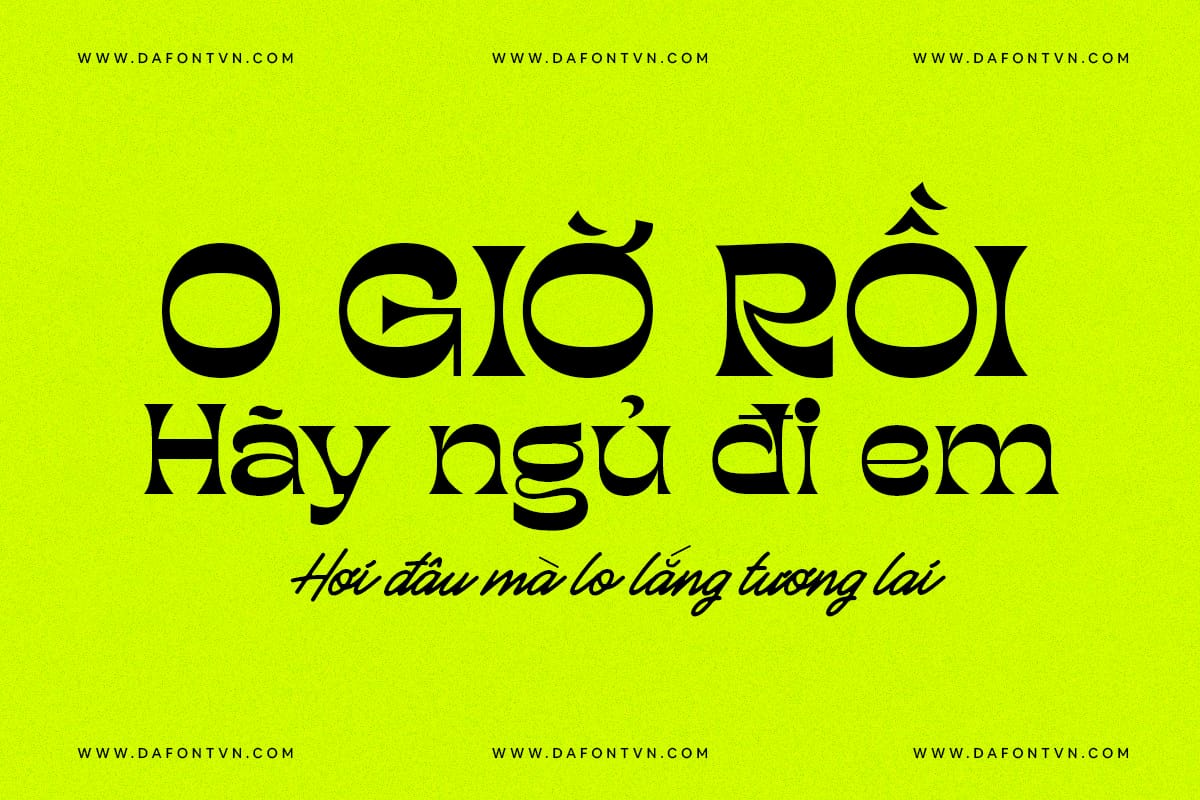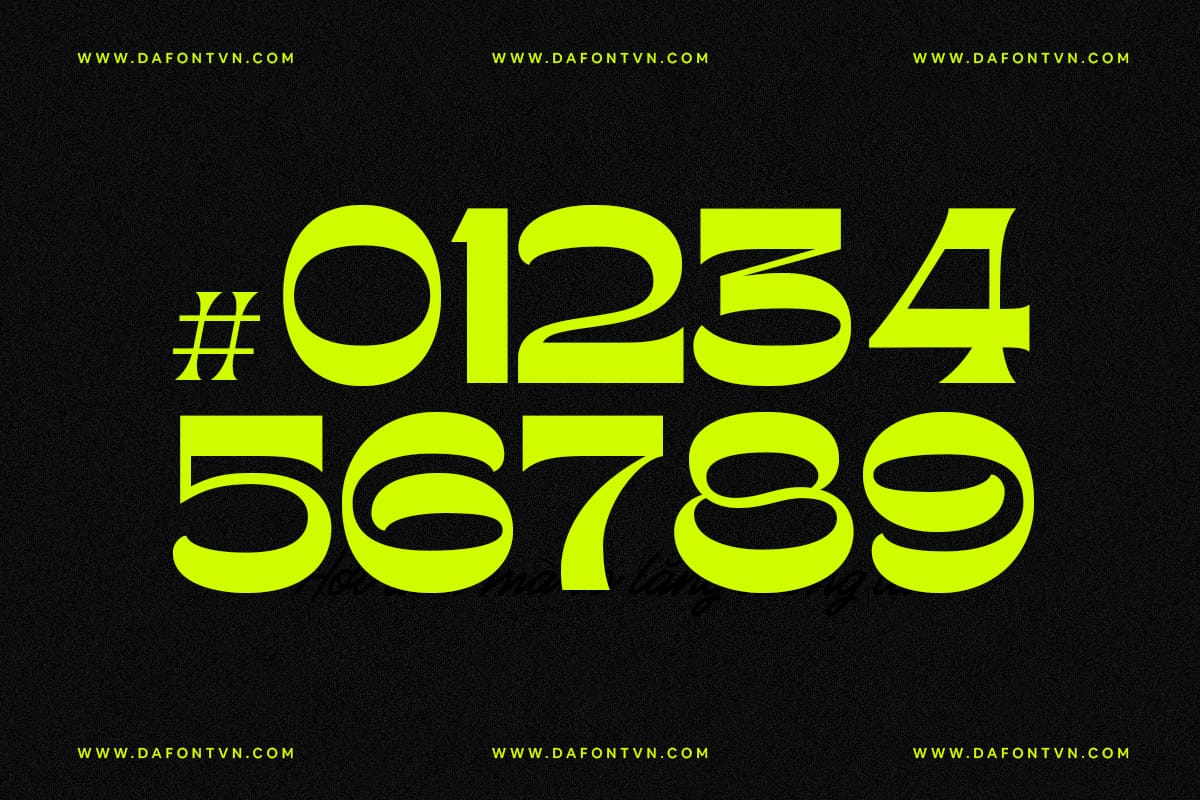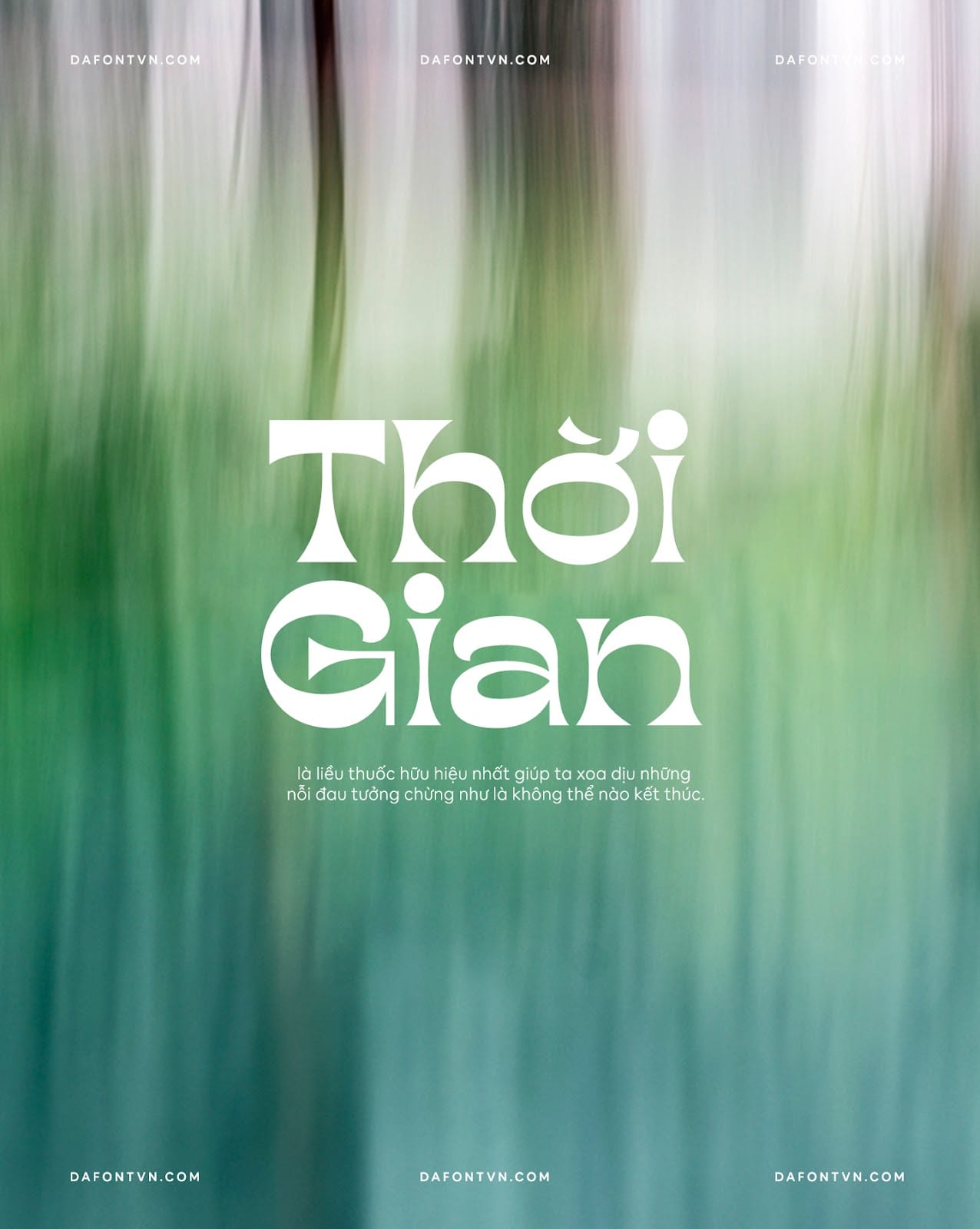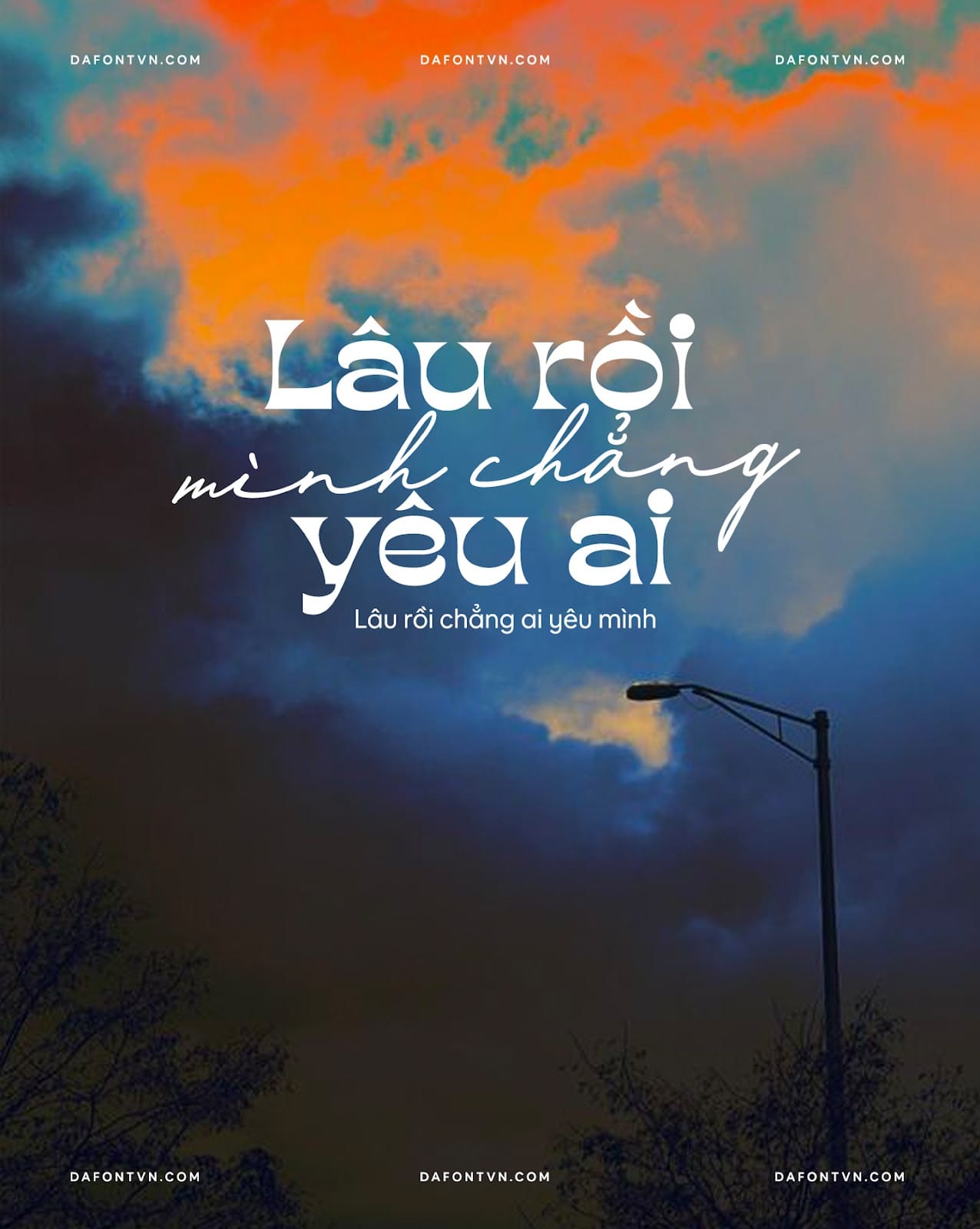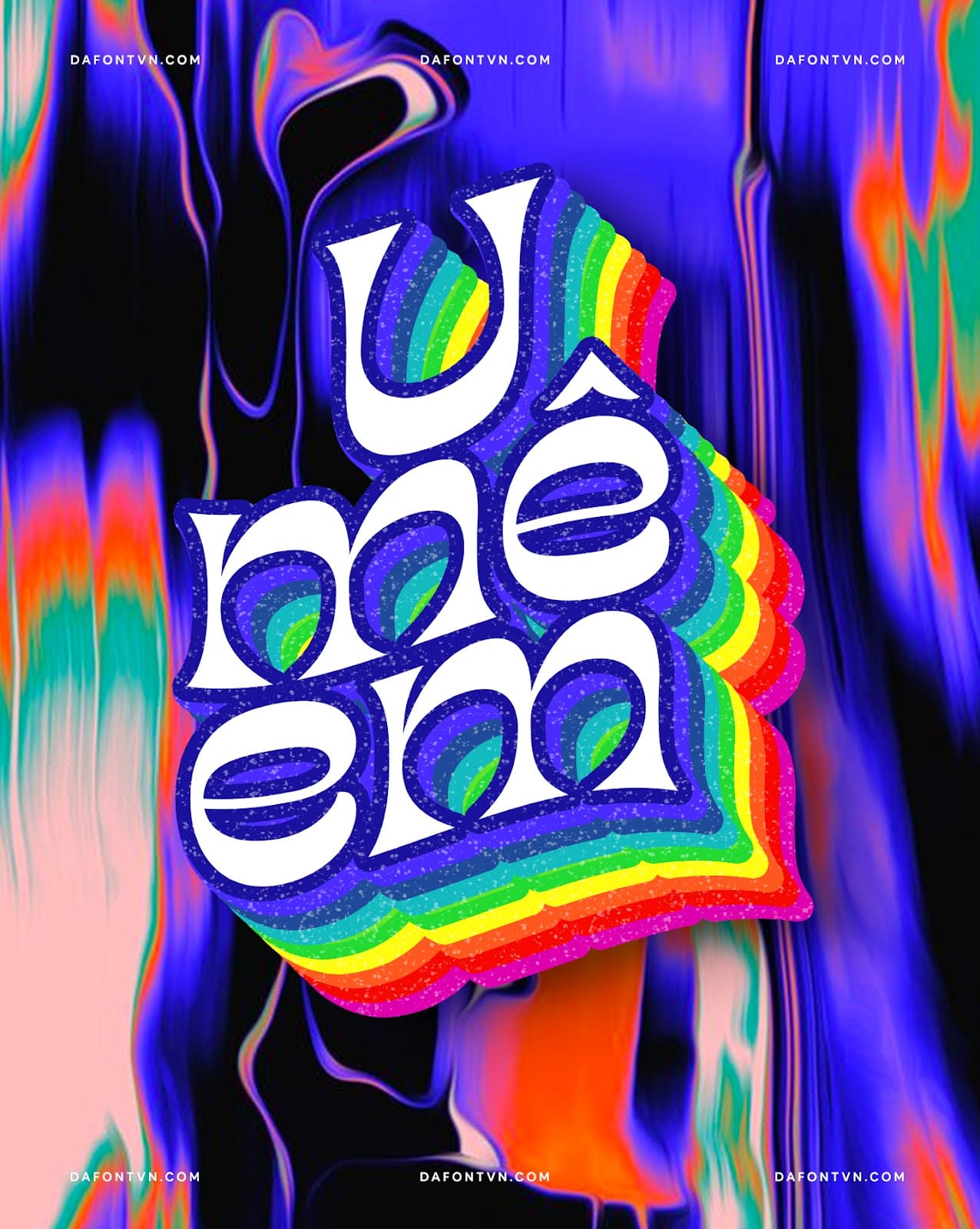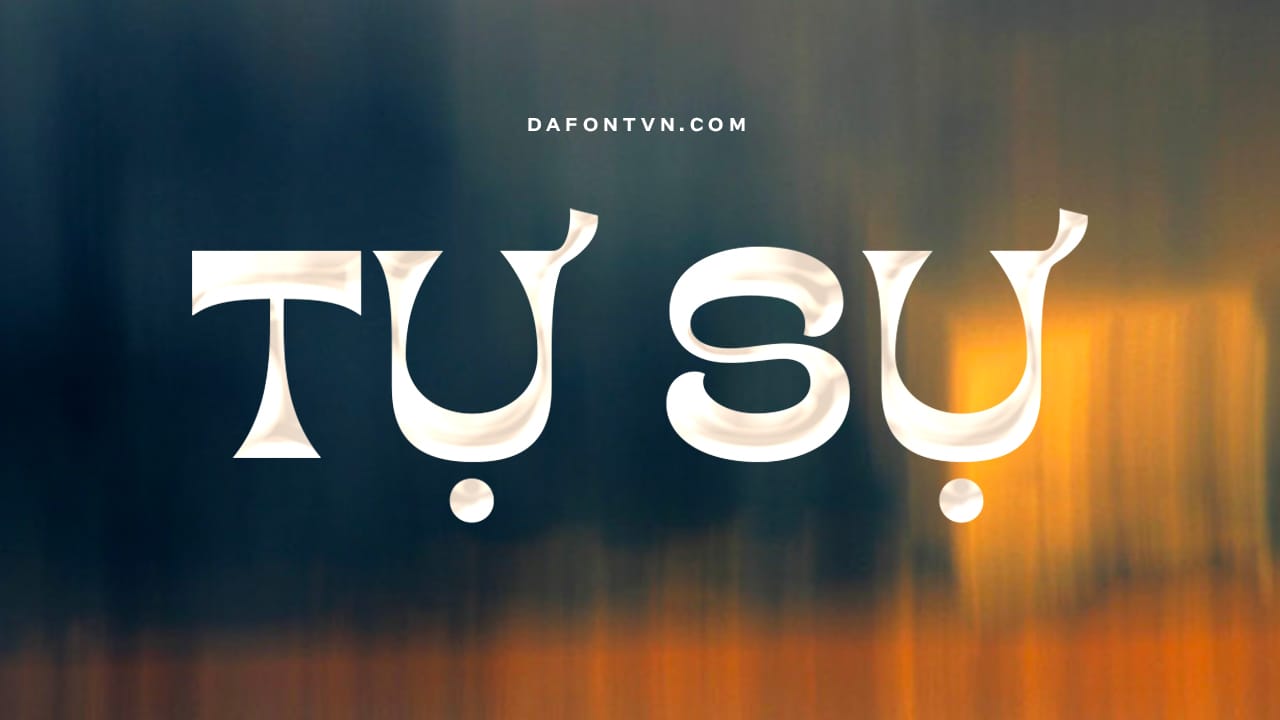
TAN – KINDRED là kiểu chữ hiển thị với reverse contrast (có độ tương phản ngược) với các nét chữ được thiết kế độc, lạ, đẹp mắt. TAN – KINDRED vừa mang phong cách cổ điển và cũng không kém phần hiện đại vì vậy bạn có thể sử dụng font chữ này cho nhiều mục đích thiết kế khác nhau.Đừng quên hãy thử kết hợp TAN – KINDRED với người anh em của nó
– một kiểu chữ tân thời cũng rất đẹp.